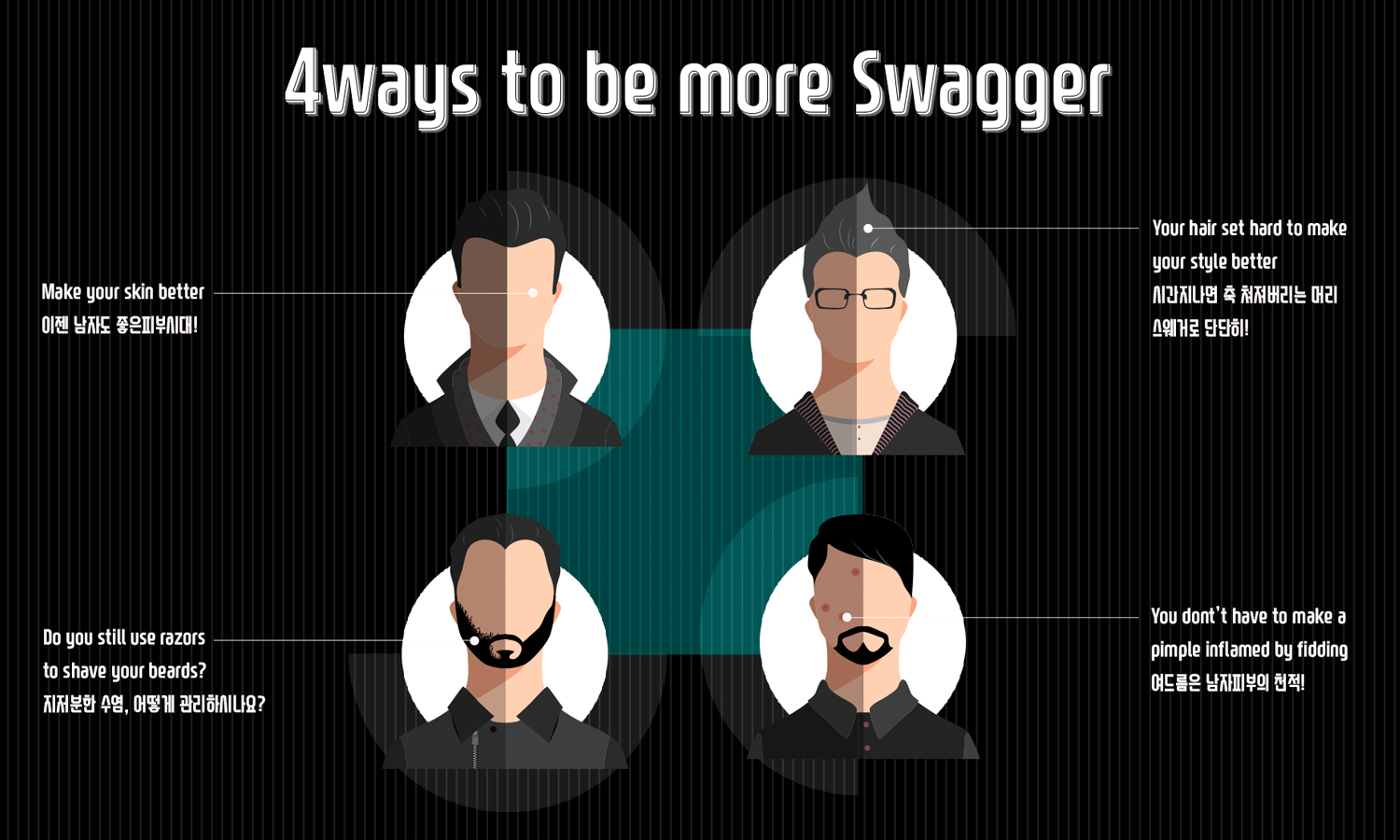
Sandoll 스웨거
산돌 스웨거는 남성 생활 건강 브랜드인 스웨거와 함께 만든 컬래버레이션 프로젝트 폰트이다.
남성을 타겟으로 하는 브랜드인 만큼 획에 무게를 두어 진함과 우직함을 나타내었고, 특징이 강한 형태가 많은 만큼 글줄이 고르게 느껴지는 것에 세심한 주의를 기울였다.